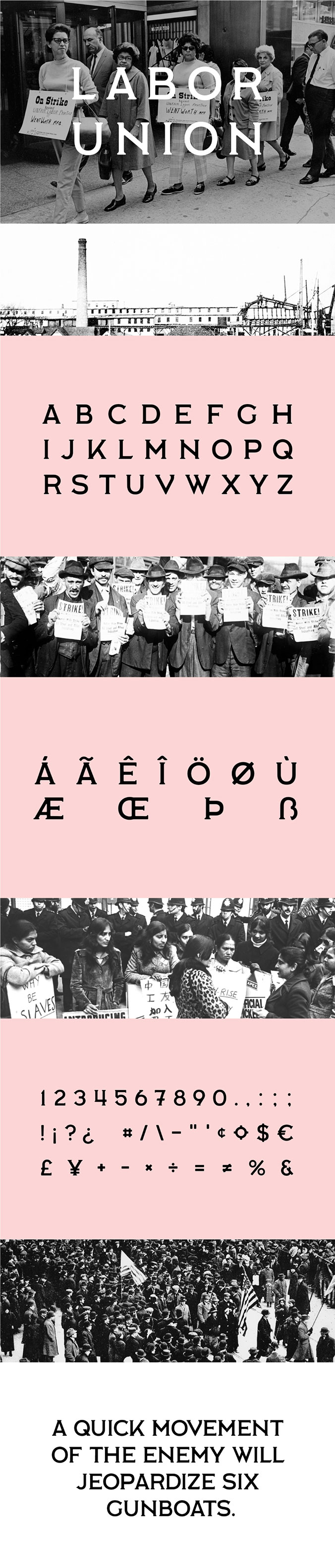
LABOR UNION字体由伊萨卡学院的学生组织“劳动行动学生”制作的。他们争取公立学校员工的公平待遇,并与当地县工人工会(汤普金斯县工人中心)紧密相连。虽然这种字体是为任何工业用途以及与工人权利和社会主义有关的任何东西而制作的,但这种字体的潜在用途是无穷无尽的 - 所有人都可以自由地享受它。支持85种不同语言的拉丁语和西里尔字符。
This font was made for the student-run group “Students for Labor Action” at Ithaca College. They fight for the fair treatment of employees at the college and are closely connected to the local county’s worker union (Tompkins County Workers Center). Although this font was made for any industrial use as well as anything pertaining to worker’s rights and socialism, the potential uses for this font are endless – and free for all to enjoy, as it should be.
Supports 85 different languages with Latin and Cyrillic characters.